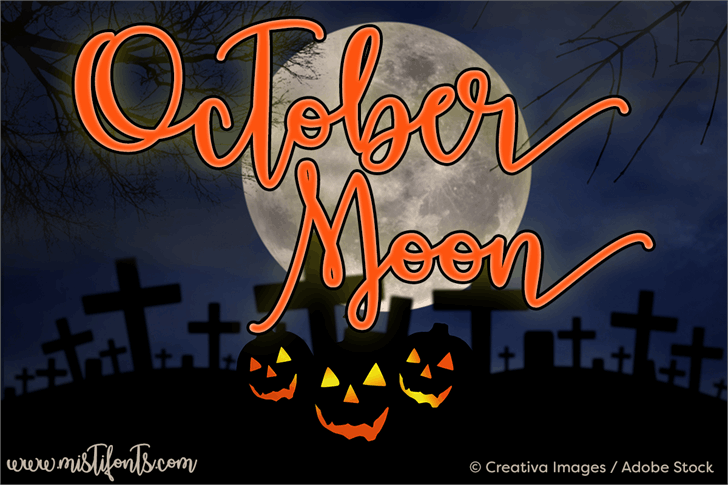
Introduzimos a October Moon Font! Esta elegante fonte script foi projetada e compartilhada pela Misti’s Fonts. Com sua característica escrita delicada e distintiva, a October Moon é perfeita para criar rótulos únicos e eventos corporativos singulares. Seus traços fluidos oferecem uma textura única que pode enriquecer qualquer projeto visual, tornando-o ainda mais atraente e memorável. Este design criativo está disponível na categoria de fontes script e está perfeito para designers em busca de um toque elegante e único nas suas criações.